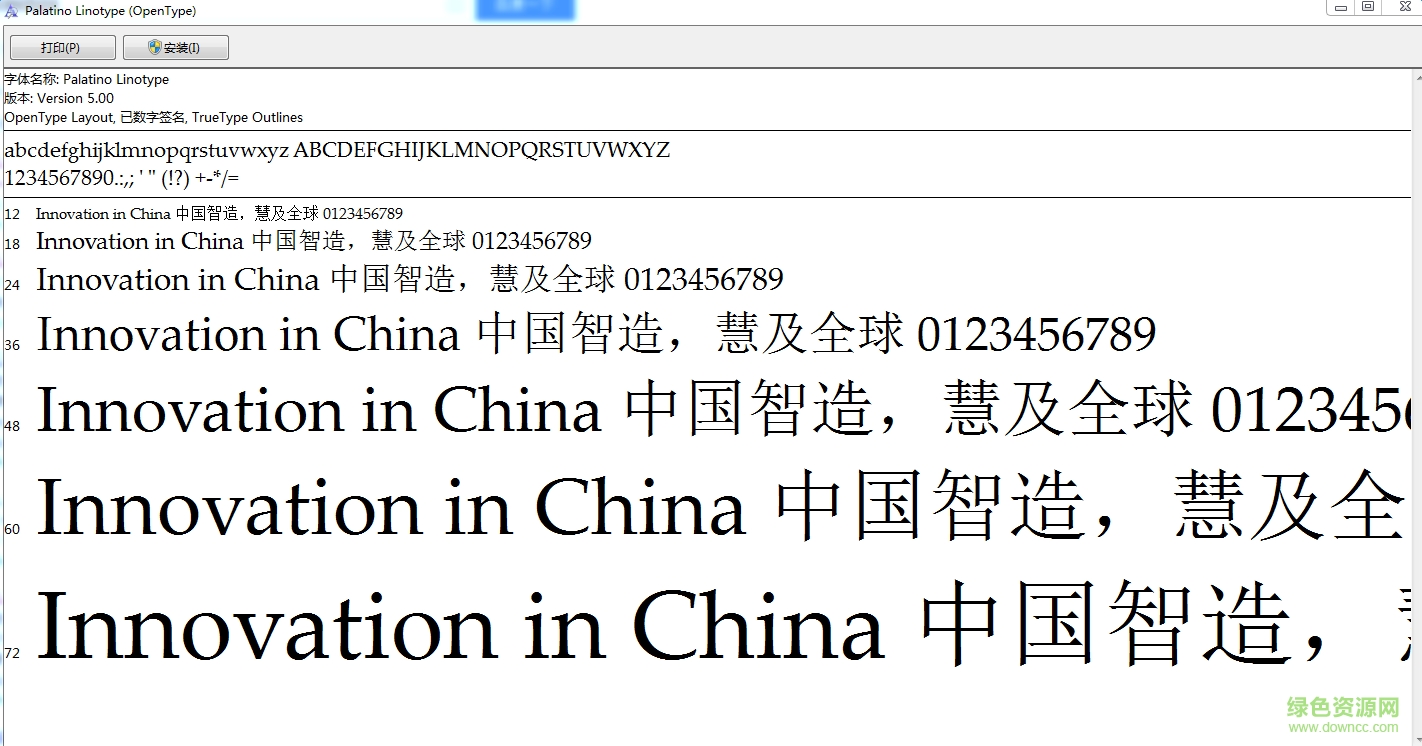
palatino linotype
palatino linotype字體是一款常見的襯線字體,字體雅致大氣,雖然很常用也是最能出彩的字體,有需要者歡迎在綠色資源網(wǎng)下載!
襯線字體介紹
襯線字體在紙媒中使用較多,在紙張上的顯示效果更加。但是在屏幕上(尤其是小屏幕上),顯示效果不是那么的好。但是依然有很多設計師喜好用襯線字體,主要多用于標題,讓標題看起來更與眾不同。